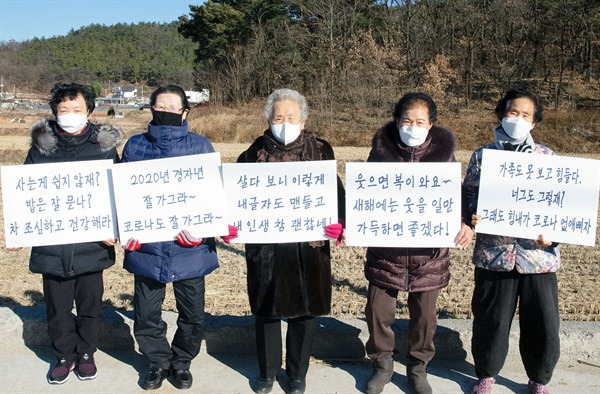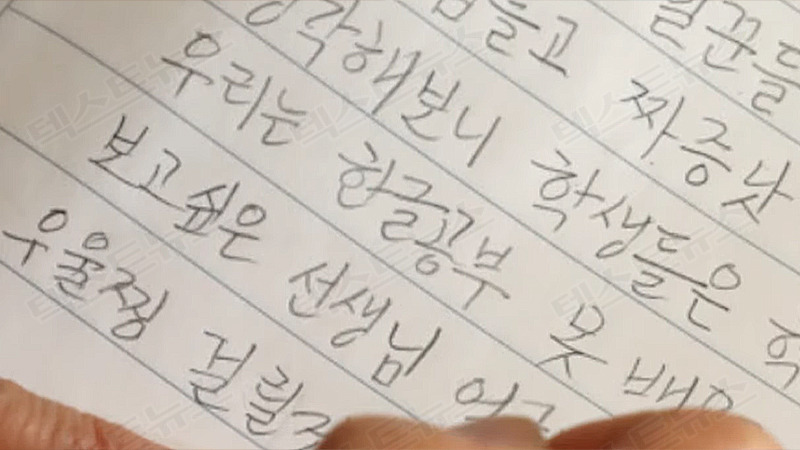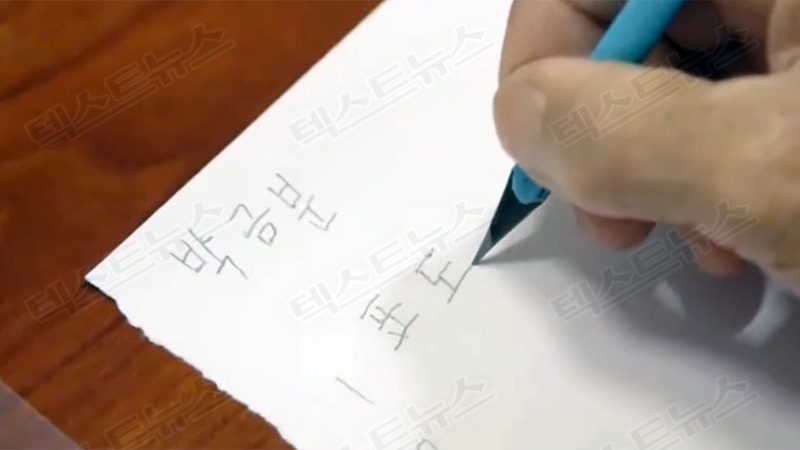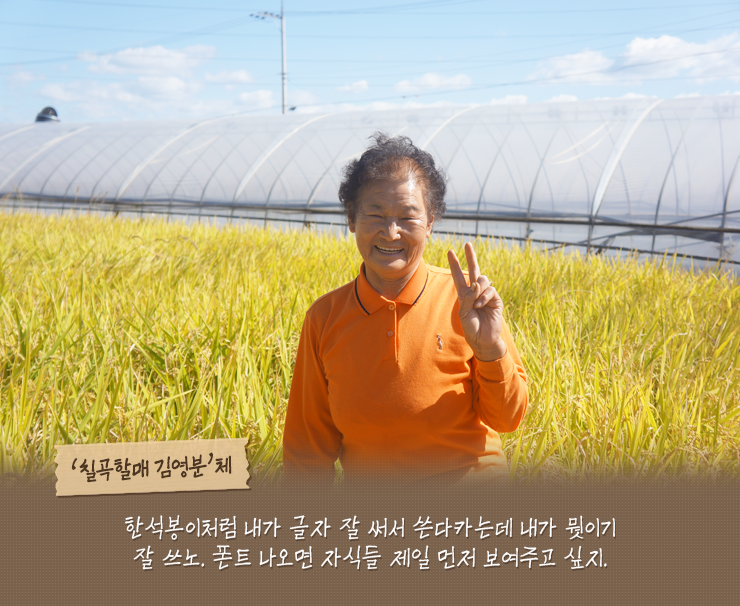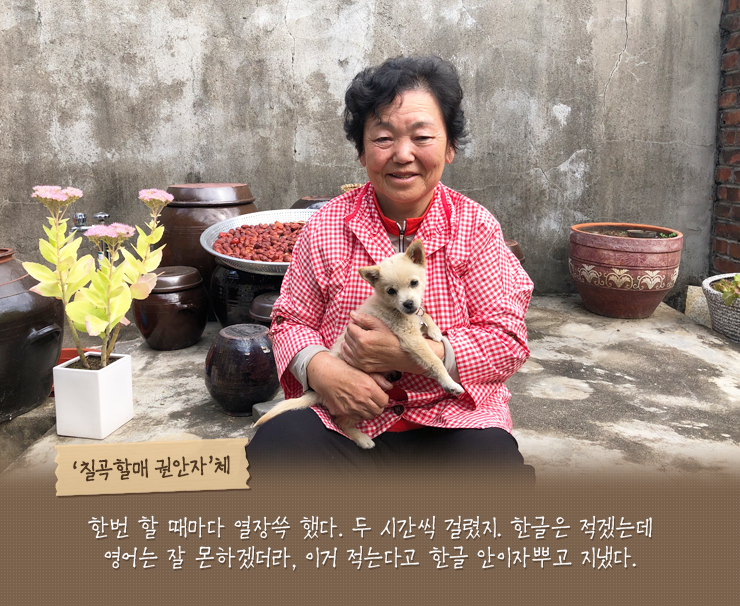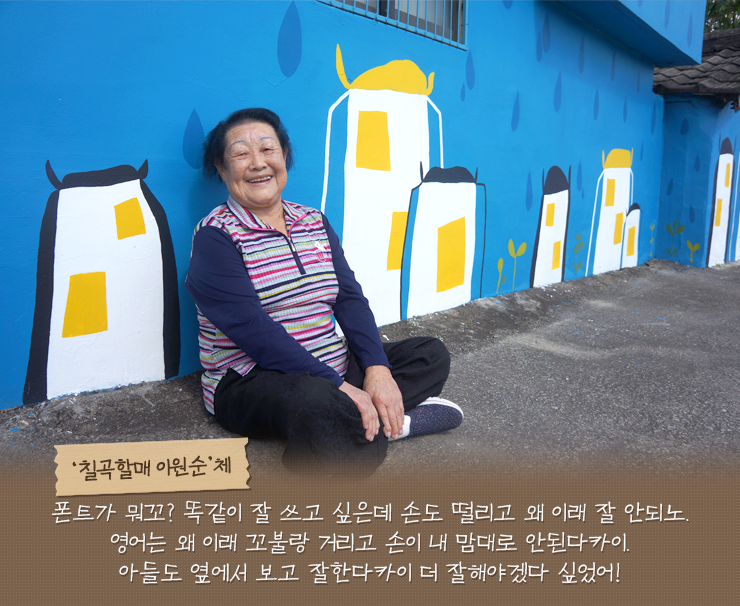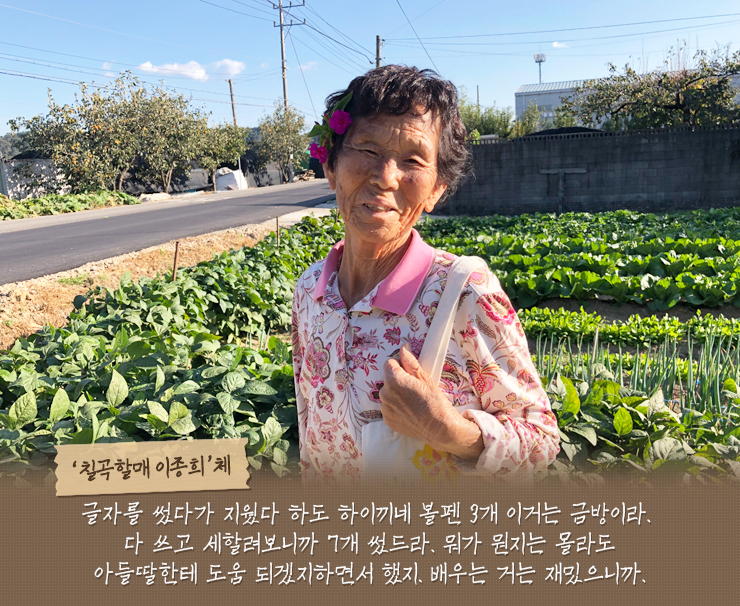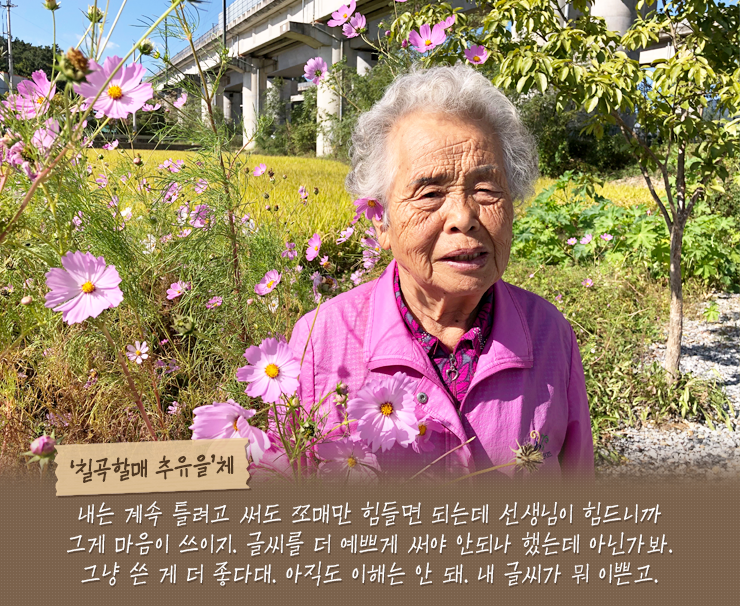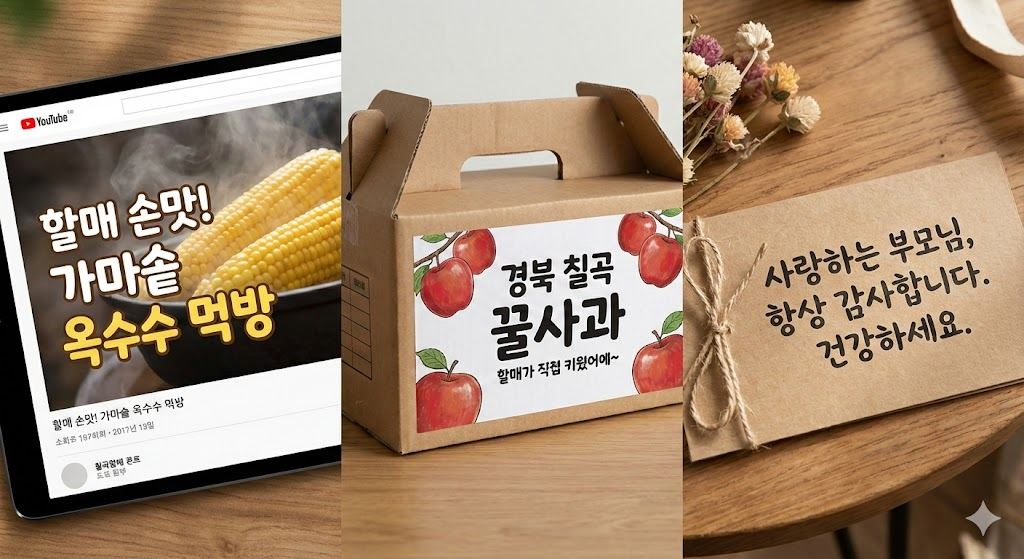
디자인 작업을 하거나 유튜브 자막을 달 때, 딱딱한 고딕체나 명조체 대신 사람의 온기가 느껴지는 손글씨 폰트가 필요할 때가 있습니다. 오늘은 단순히 예쁜 글씨를 넘어, 가슴 뭉클한 사연과 역사가 담긴 아주 특별한 폰트를 소개해 드리려고 합니다.
바로 경상북도 칠곡군 할머니들의 피와 땀, 그리고 웃음이 담긴 '칠곡할매 폰트'입니다. 한컴오피스에도 탑재될 만큼 유명해진 이 글꼴의 탄생 배경부터 다운로드 방법, 그리고 가장 중요한 라이선스 범위까지 꼼꼼하게 정리해 드립니다.
🎯 칠곡할매 폰트란?
칠곡할매 서체는 전문 폰트 디자이너가 만든 글씨가 아닙니다. 칠곡군에서 운영하는 '성인문해교육'을 통해 뒤늦게 한글을 깨치신 할머니들의 손글씨입니다.
평생 까막눈으로 사시다 칠순, 팔순이 넘어서야 연필을 잡고 "가나다라"를 배우신 할머니들. 꾹꾹 눌러쓴 글씨 하나하나에는 할머니들의 굴곡진 인생과 배움에 대한 열정이 고스란히 녹아 있습니다.
칠곡군은 문해교육을 받는 할머니 400여 분 중 개성 있는 글씨체를 가진 다섯 분을 선정하여, 약 4개월간의 작업을 거쳐 이 아름다운 디지털 서체를 완성했습니다. 이제는 전 국민이 사랑하는 '국민 폰트'가 되었지요.
이 폰트들은 삐뚤빼뚤하지만 정겹고 따뜻한 ‘사람 냄새 나는 손글씨’로, 디지털 세상에서 잊히기 쉬운 감성을 되살리는 목적으로 만들어졌습니다. 제작 배경에는 단순한 서체 개발이 아닌, 노년 세대의 삶과 역사를 기억하고 되새기자는 의지가 담겨 있습니다.
👵 다섯 분의 할머니, 다섯 가지 개성
칠곡할매 글꼴은 총 5종으로 구성되어 있습니다. 각 서체마다 할머니들의 성함이 붙어 있어 더욱 친근하게 느껴집니다.
- 칠곡할매 권안자체: 획의 굵기가 일정하고 또박또박하여 가독성이 좋습니다.
- 칠곡할매 김영분체: 둥글둥글하고 귀여운 느낌이 강해 예능 자막이나 감성적인 문구에 어울립니다.
- 칠곡할매 이원순체: 거침없고 시원시원한 필체가 특징입니다.
- 칠곡할매 이종희체: 삐뚤빼뚤한 듯하지만 정겨움이 가장 많이 묻어나는 서체입니다.
- 칠곡할매 추유순체: 단정하면서도 옛 서예 글씨 같은 고전미가 느껴집니다.
이 폰트들은 정형화된 컴퓨터 글씨와 달리, '리을(ㄹ)'이나 '이응(ㅇ)'의 모양이 제각각이라 더욱 자연스러운 손글씨 느낌을 줍니다.
📚 제작 배경 — “문해교육 → 손글씨 → 폰트”의 여정
- 2008년부터 칠곡군에서는 ‘성인 문해교실’을 통해, 글을 배우지 못했던 어르신들이 한글을 배울 수 있는 기회를 마련했습니다.
- 그중에서도 글씨체가 개성 있고 따뜻한 할머니 다섯 분을 선정하여, 이들의 손글씨를 디지털 폰트로 만들기로 결정했습니다.
- 할머니들은 각자 약 2,000여 장의 종이에 반복해서 연습하며 글씨를 썼고, 그 결과물이 모여 지금의 칠곡할매서체가 탄생했습니다.
- 이 프로젝트는 단순한 디자인 작업이 아닌, “삶의 역사와 기억을 기록하는 문화유산”으로 평가받았으며, 많은 사람들에게 감동과 울림을 주었습니다.
💡 활용 팁 및 활용 사례
- 따뜻하고 인간적인 감성을 살리고 싶을 때
— 손글씨 특유의 어딘가 투박하지만 정겨운 느낌 때문에, 에세이, 편지, 전시 포스터, 커뮤니티 콘텐츠 등에 잘 어울립니다. - 출판물, 리플렛, 브로셔 디자인
— 감성 기반의 인쇄물이나 예술/문화 행사 안내지 등에 사용하면 “사람 냄새 나는” 분위기를 연출할 수 있습니다. - 웹사이트 및 블로그 디자인
— 웹페이지 타이틀, 배너, 캘리그래피 요소 등에 사용하면 디지털이지만 손글씨의 따스함을 더할 수 있습니다. - 영상 자막 / 오프닝 / 엔딩 크레딧
— 영상 콘텐츠에서도 사용이 가능하므로, 브이로그, 다큐, 로컬 문화 콘텐츠 등에서 감성적인 터치를 줄 수 있습니다.
📝 마무리하며
칠곡할매서체는 단순한 글꼴이 아니라, 한글을 새로 배운 어르신들의 삶과 기억, 그리고 열정이 담긴 ‘산 문화유산’입니다. 손글씨의 따뜻함과 인간미를 살리고 싶다면 — 블로그, 디자인, 영상, 출판 등 다양한 매체에서 이 폰트를 활용해 보세요.
좋은 폰트, 칠곡할매서체 — 꼭 한 번 사용해 보시길 추천드립니다. 🙏